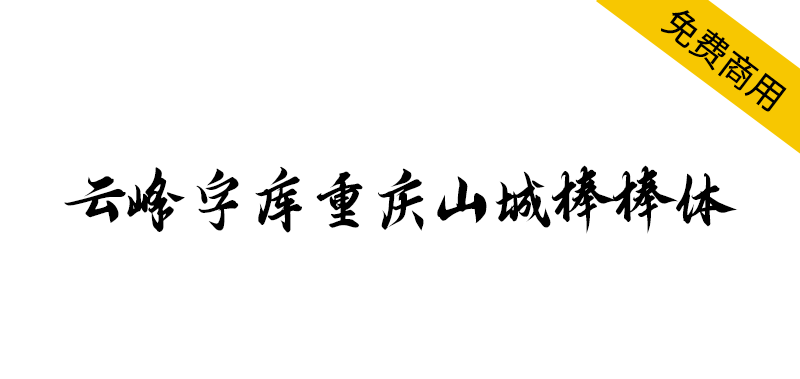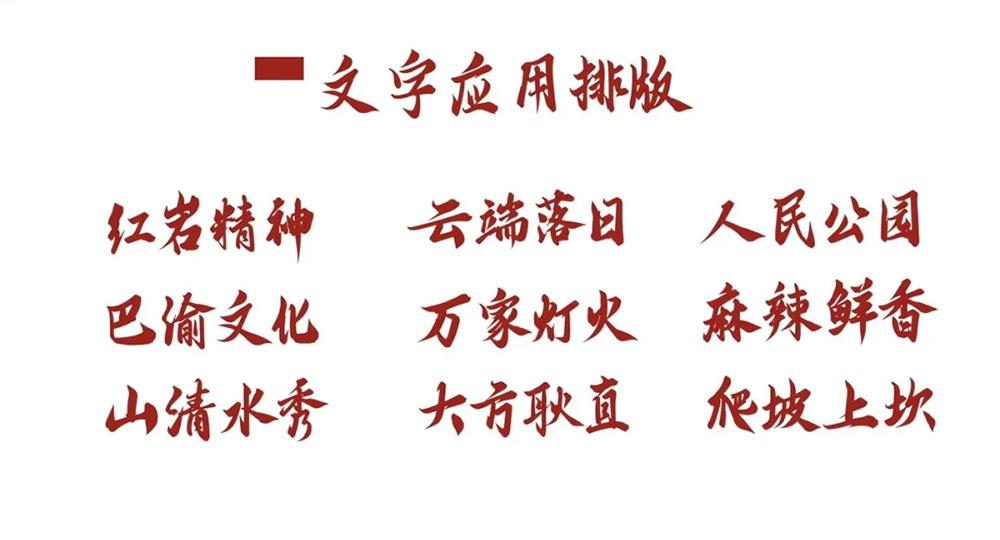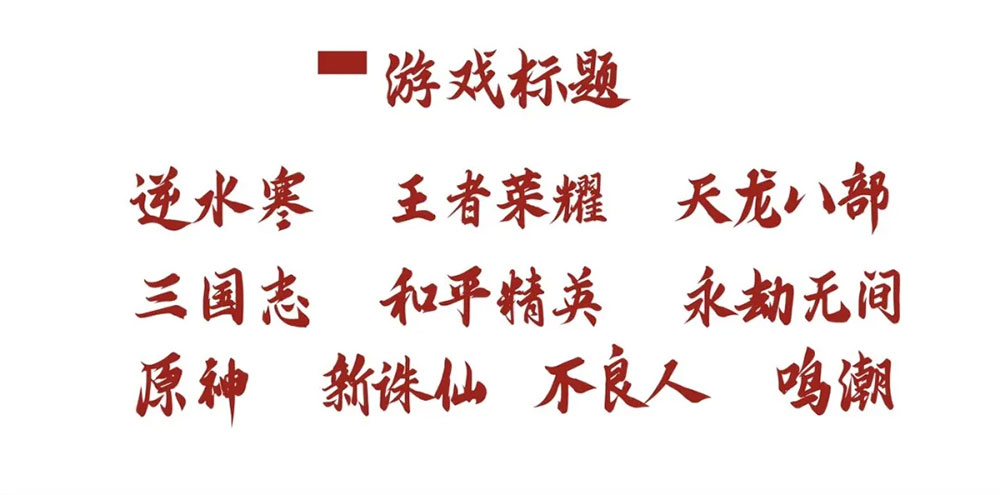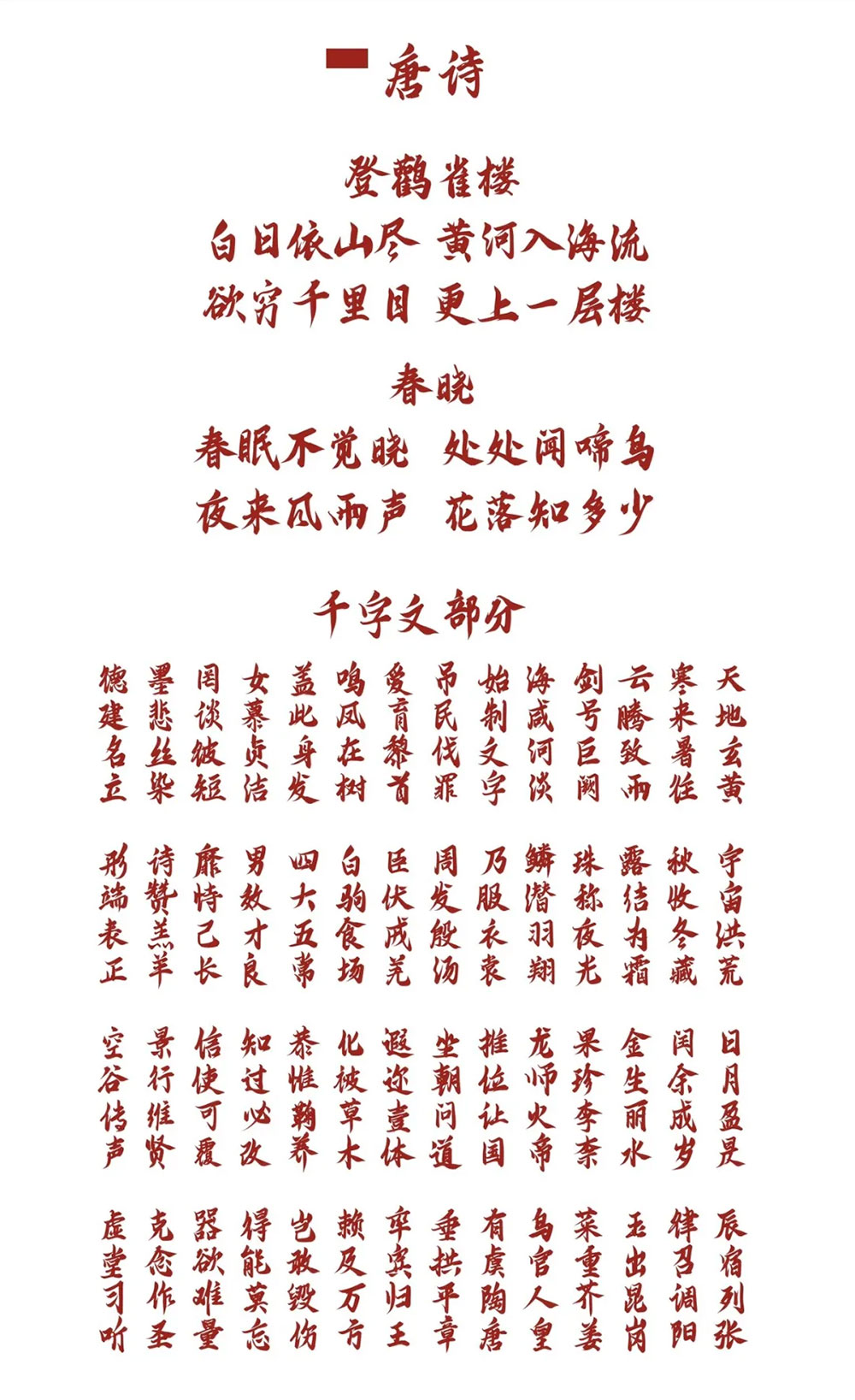
各位新老朋友大家好,很高兴再次和大家见面,先自我介绍一下:云峰字库,一个来自重庆本土的字库小品牌,一个人,一台电脑,组成了它,因热爱而存在,在此之前,已经发布了三款免费商用字体:云峰飞云体、云峰静龙行书、云峰寒蝉体,承蒙厚爱,云峰飞云体得到了大家的认可,被运用于影视、包装、平面、短视频等渠道,感谢大家的认可。
纪念重庆消失的职业”山城棒棒军“,这款字为重庆,行千里致广大,这款字体不收费,全凭看官打赏,得到各位看官的打赏,我会更有动力做优惠字体,谢谢!